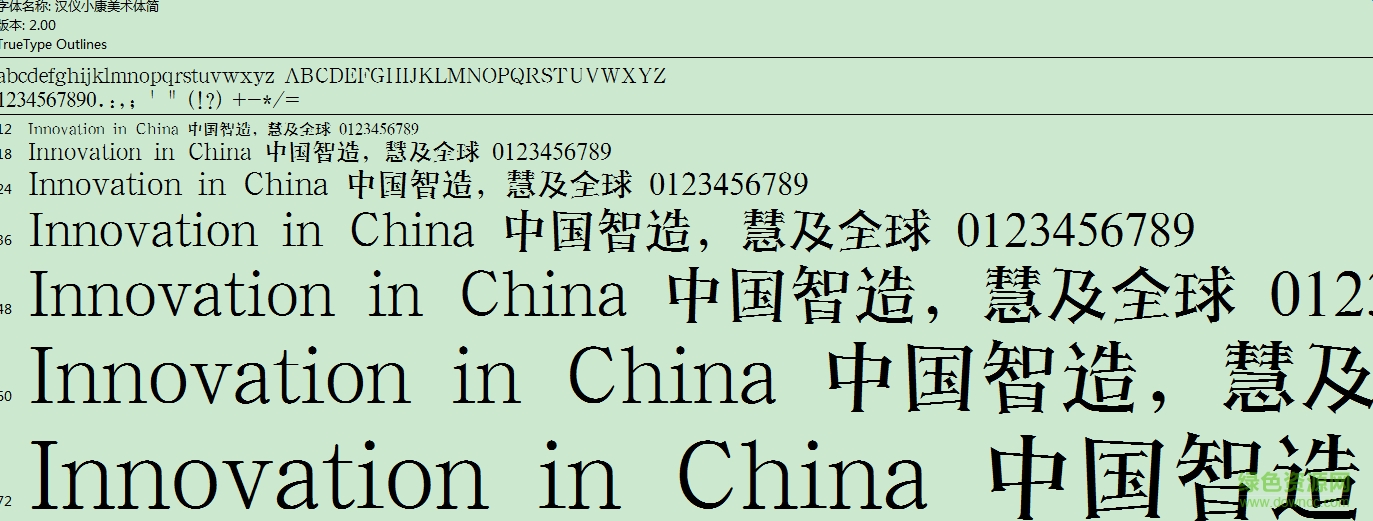
hyt1gj是什么字体?hyt1gj字体又叫汉仪小康美术体,该字体的结构不是非常合乎标准,但给人一种自由随性的感觉,可用于漫画设计、游戏、杂志等方面,需要更多美术字体的朋友快来绿色资源网下载吧!
1.文字的主要功能是在视觉传达中向大众传达作者的意图和各种信息,要达到这一目的必须考虑文字的整体诉求效果,给人以清晰的视觉印象。
2.在视觉传达的过程中,文字作为画面的形象要素之一,具有传达感情的功能,因而它必须具有视觉上的美感,能够给人以美的感受……